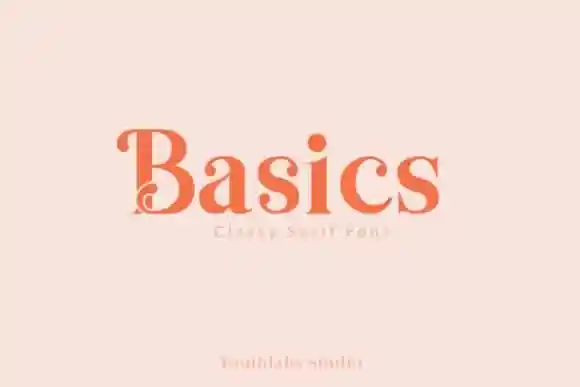
Basics Display Font – Download Grátis
Basics Display Font é uma fonte serif com propriedades de tipo display que traz tanto ligaturas quanto alternativas de caracteres, garantindo diversidade em seus projetos. Esta fonte serif se destaca por sua sofisticação e originalidade, repleta de swashes elegantes e modernas, criando um toque nostálgico ao mesmo tempo, perfeito para qualquer aplicação. Perfeita para criar cartelas de casamento, títulos e logotipos, Basics Display Font oferece um look refinado e sutíl com uma ampla versatilidade que irá surpreender você. Seja você um designer profissional ou iniciante, ele certamente o deixará impressionado.